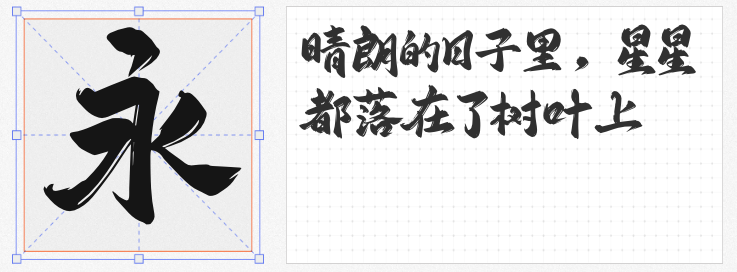
在海报设计的视觉表达中,书法字体以其独特的文化韵味与艺术张力,成为传递情感、烘托氛围的点睛之笔。本文精选四款免费商用书法字体,兼具传统美学与现代设计感,助您轻松打造令人过目难忘的海报作品。
由字库星球与甜奈网络联合研发的字库星球飞扬体,将传统书法的潇洒写意与现代设计理念完美融合。其笔画灵动多变,起承转合间充满韵律感,整体结构如行云流水般自然流畅。无论是科技主题的未来感海报,还是节日庆典的欢快氛围营造,字库星球飞扬体都能以飒爽流畅的视觉气场传递热情洋溢的情感,尤其适合需要突出动态感与艺术气质的设计场景。
马善政毛笔楷书以传统对联字体为灵感,笔画粗壮有力,结构端庄稳重,呈现出磅礴大气的视觉效果。这款字体自带文化厚重感,适合用于传统节日海报、文化展览宣传或需要传递庄重祝福的场景。其生机勃勃的笔触与恢宏气势,能瞬间提升海报的视觉冲击力。
基于马善政毛笔楷书优化拓展的玄冬楷书,在保留原版厚重气质的基础上,修复了字形错误并新增竖排排版功能,更贴合中文排版习惯。无论是古典诗词海报的竖排文字,还是需要严谨结构的标题设计,玄冬楷书都能以清晰的笔画与稳定的结构,为作品增添一份典雅与秩序感。
程荣光刻楷作为一款免费商用楷体,以简洁清晰的笔画与规整的结构著称。其版权已正式注册,设计师可放心用于商业项目。这款字体适合需要突出信息可读性的海报设计,如活动公告、产品说明等场景,既能传递专业感,又能通过楷书的温润气质拉近与观众的距离。